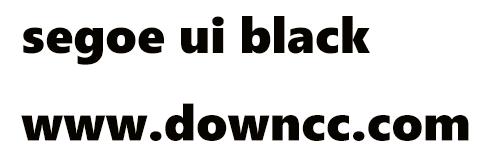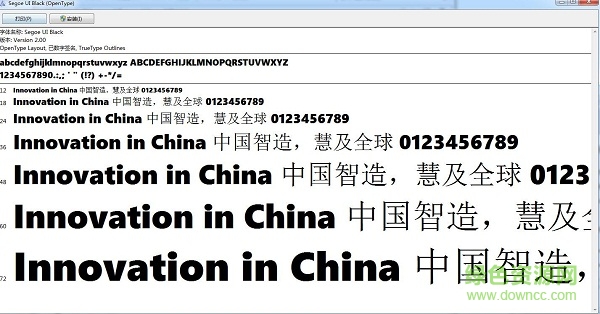
segoe ui black黑體字體是一款英文古典體,也就是人文主義無襯線字體,字形端正嚴(yán)謹(jǐn),線條變化曲率相同,均勻美觀,實(shí)用性強(qiáng),需要的朋友快來下載吧!
無襯線體(Sans-serif)專指西文中沒有襯線的字體,與漢字字體中的黑體相對(duì)應(yīng),古典體是無襯線字體中最具書法特色的,有更強(qiáng)烈的筆畫粗細(xì)變化和可讀性。